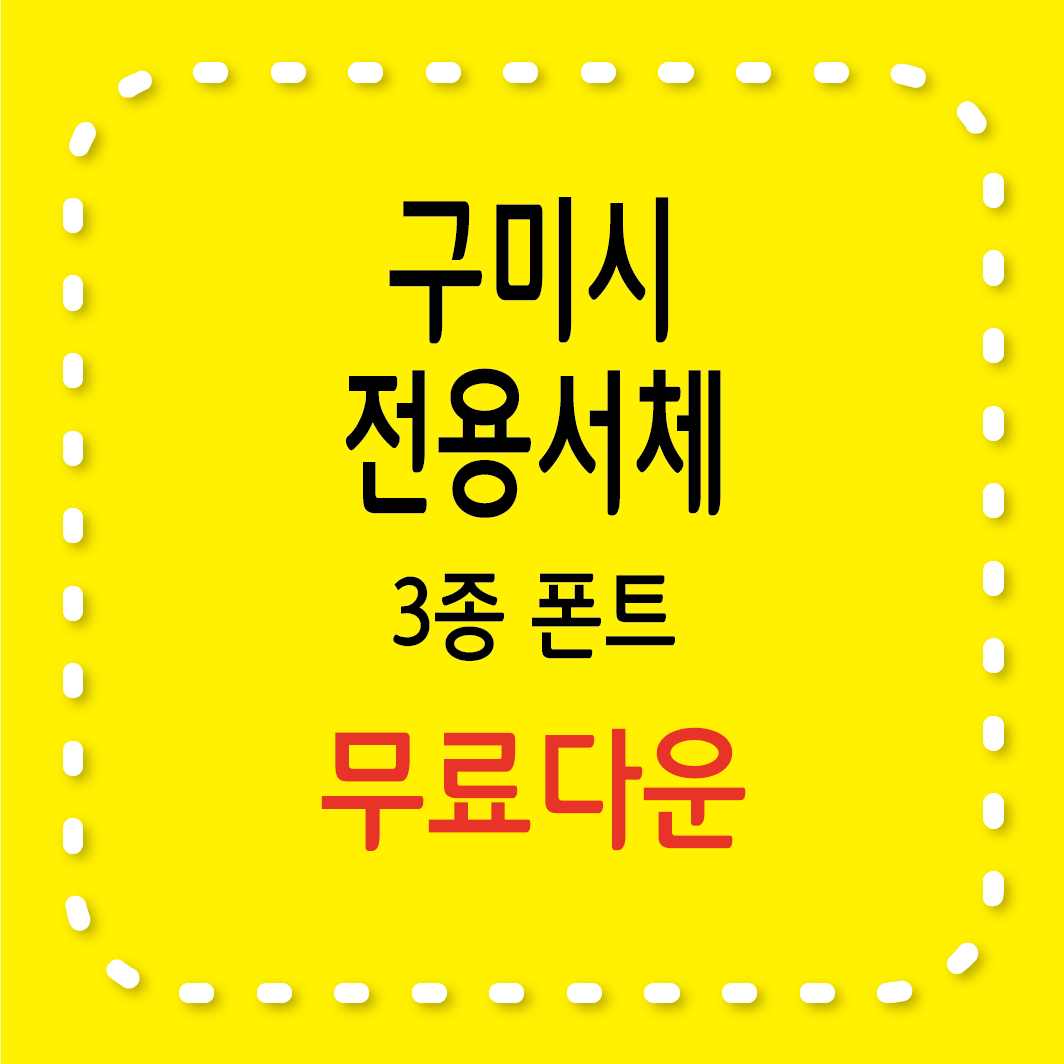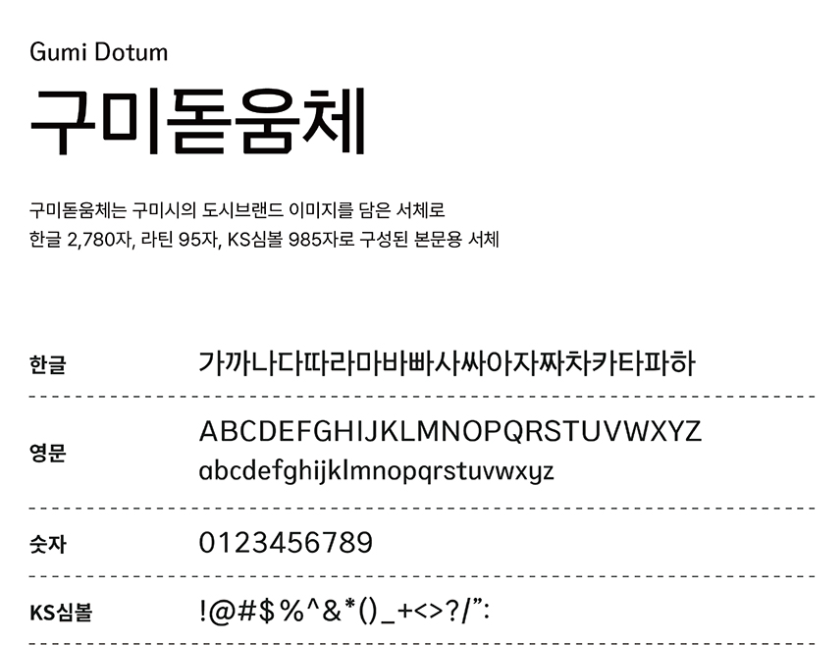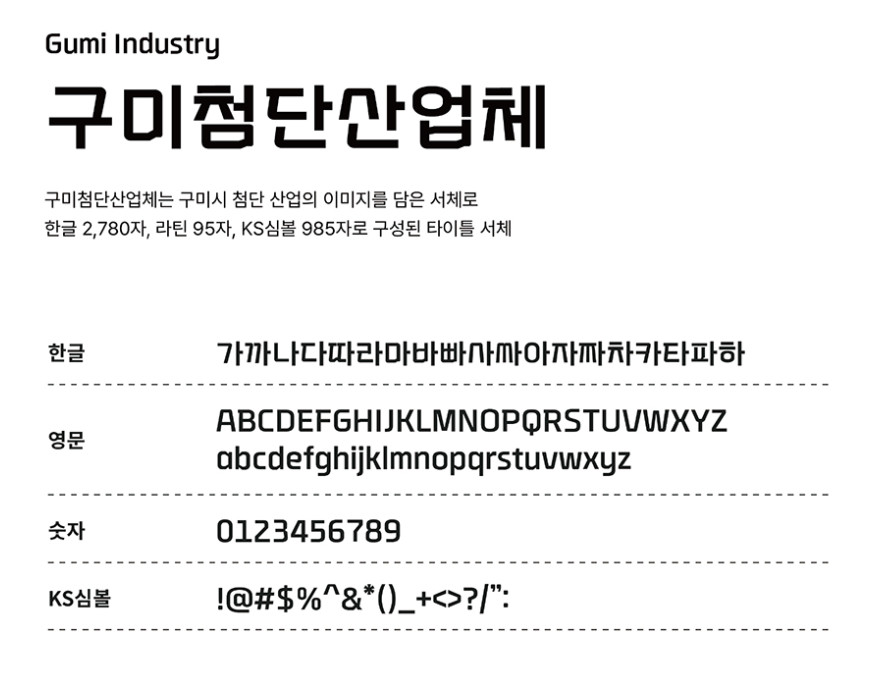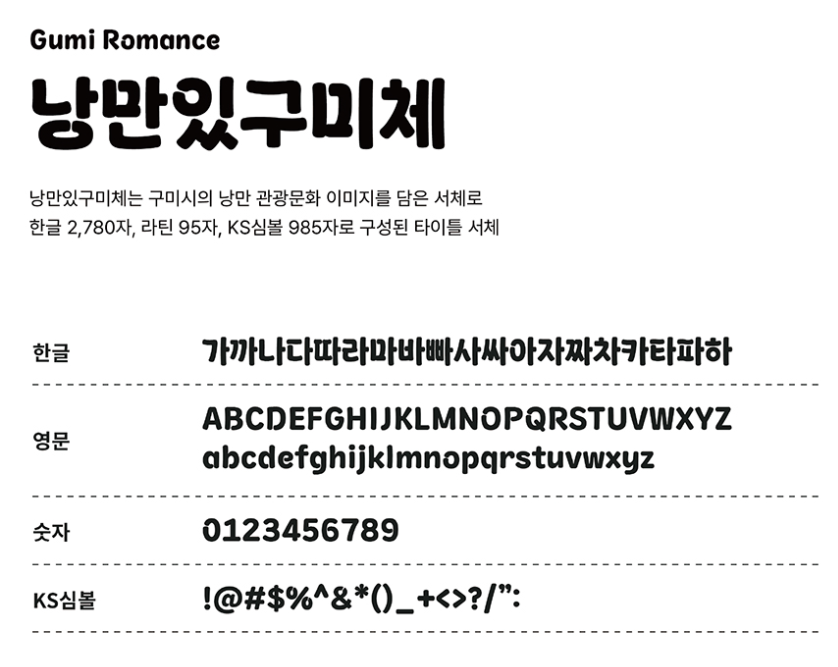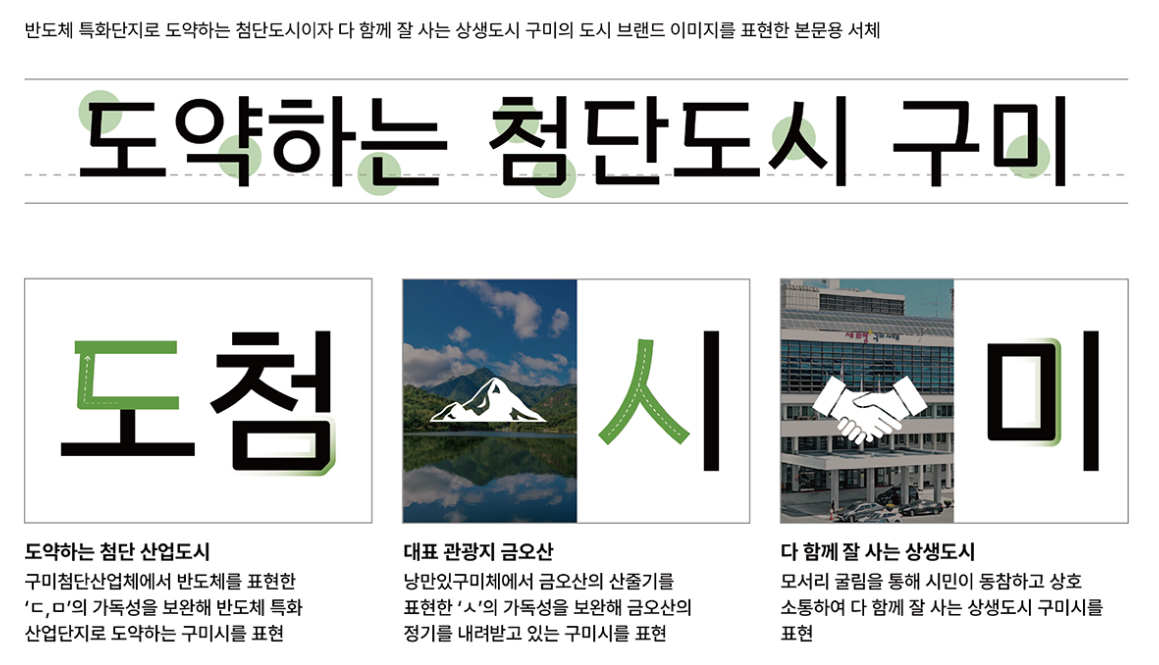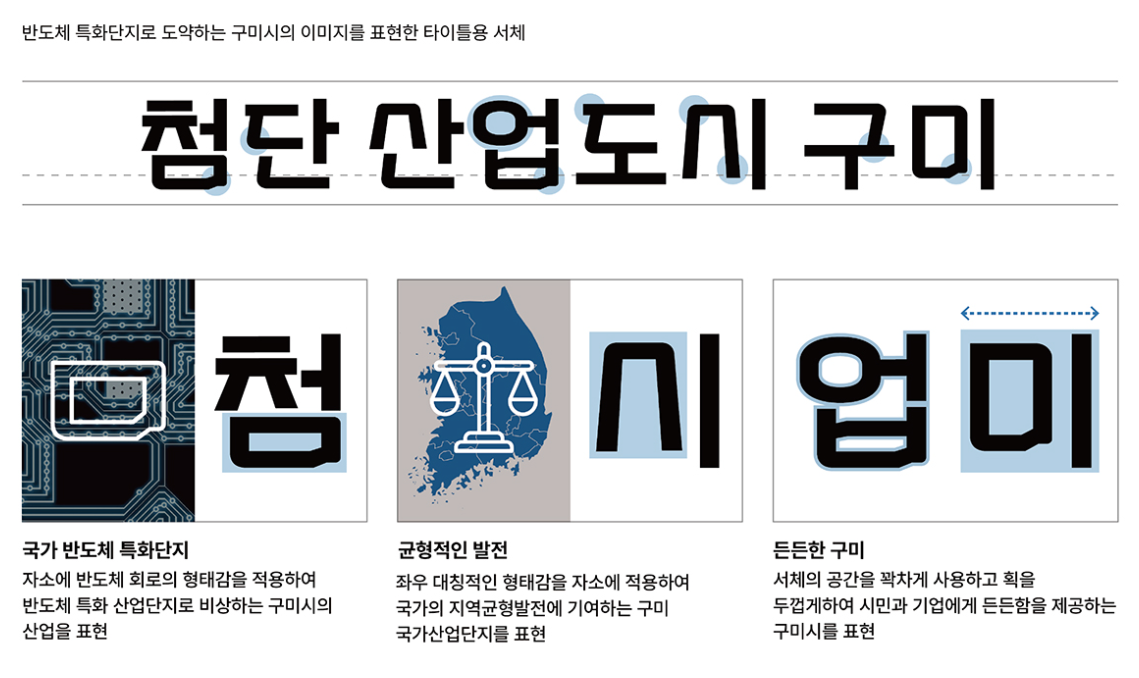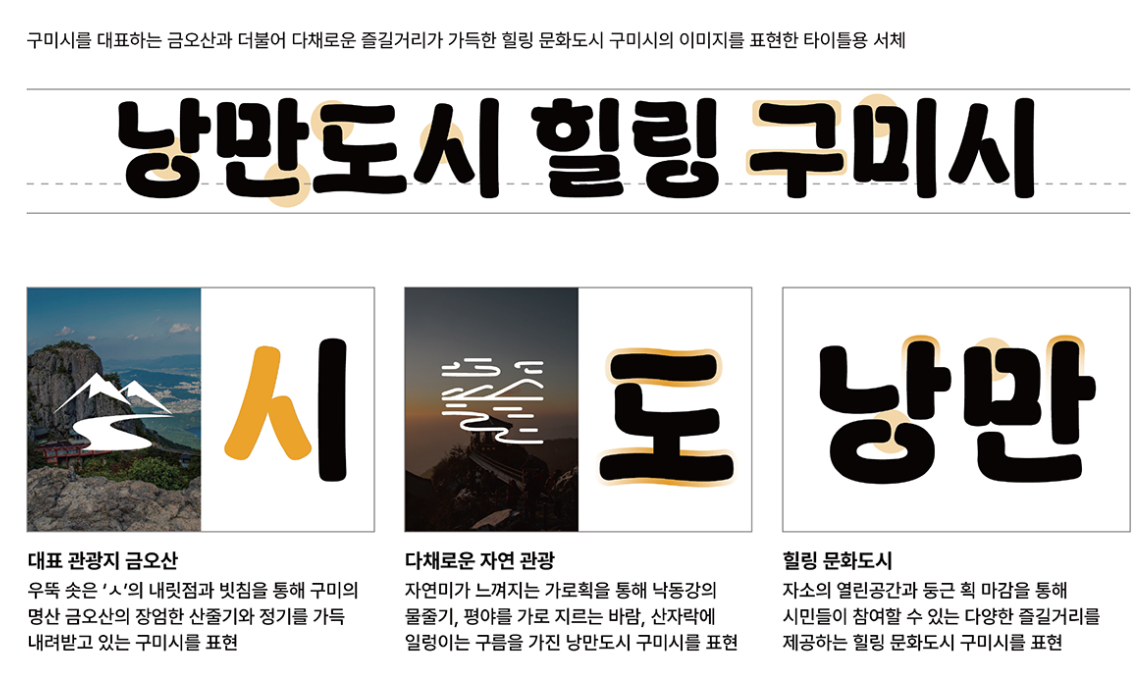
구미시 전용서체란?
도시의 산업적 이미지와 지역 상징성을 시각적으로 담아낸 서체로, 본문용과 제목용으로 각각 사용할 수 있도록 세 가지 스타일이 제공됩니다.
서체 종류 및 용도
- 구미돋움체 – 본문용 (가독성 중심)
- 구미첨단산업체 – 제목용 (산업도시 이미지 반영)
- 낭만있구미체 – 제목용 (관광도시 감성 반영)
각 서체는 한글 2,780자, 영문 95자, KS 심볼 985자 등으로 구성되어 있어, 실무에서 사용하기에 매우 풍부한 문자 지원을 제공합니다.
주요 디자인 특징
✔️ **산업도시 구미**를 상징하는 첨단 이미지 표현
✔️ **관광도시 감성**을 살린 부드럽고 개성 있는 형태
✔️ 본문용 서체는 장시간 읽기에도 적합하도록 설계
✔️ 타이틀용 서체는 브랜딩, 광고에 활용하기 좋음
또한 모든 서체는 고정폭, 시각 중심 정렬을 기반으로 한 구조로 설계되어 있어, 디자인 일관성이 뛰어납니다.
‘구미시 전용서체’는 도시의 정체성과 실용성을 모두 담은 고품질 무료 폰트입니다.